Top 15 font chữ cho CV, portfolio cá nhân và hồ sơ năng lực freelancer
Gợi ý 15 font TH Việt hóa cho CV, resume, portfolio cá nhân, hồ sơ năng lực freelancer và profile chuyên gia.
CV, portfolio cá nhân và hồ sơ năng lực freelancer đều có một điểm chung: người xem thường chỉ lướt rất nhanh trước khi quyết định đọc kỹ hơn. Vì vậy, font chữ cần giúp thông tin rõ ràng, chuyên nghiệp và có cá tính vừa đủ. Một CV quá cầu kỳ có thể khó đọc; một portfolio quá đơn giản lại dễ bị chìm giữa hàng chục hồ sơ khác.
Bài viết này gợi ý 15 font TH Việt hóa phù hợp cho CV, resume, portfolio cá nhân, hồ sơ năng lực freelancer, media kit và profile chuyên gia. Danh sách tập trung vào font sans-serif sạch, serif thanh lịch và một font chữ ký để tạo điểm nhấn cá nhân. Khi dùng, anh nên xác định rõ vai trò: font cho tên cá nhân, font cho heading, font cho nội dung kinh nghiệm và font cho các con số nổi bật.
Tiêu chí chọn font CV và portfolio cá nhân
Font cho CV cần đọc nhanh, rõ dấu tiếng Việt và không làm nhà tuyển dụng mệt mắt. Font cho portfolio thì có thể cá tính hơn, nhưng vẫn phải giúp case study, mô tả dự án, vai trò và kết quả được trình bày mạch lạc. Với hồ sơ năng lực freelancer, font còn phải truyền được cảm giác đáng tin: khách hàng cần nhìn thấy sự chuyên nghiệp trước khi xem đến bảng giá hoặc dự án mẫu.
Top 15 font TH cho CV, portfolio và hồ sơ freelancer
1. TH Legacy Sans - CV hiện đại, hồ sơ ứng tuyển startup, portfolio online và profile LinkedIn
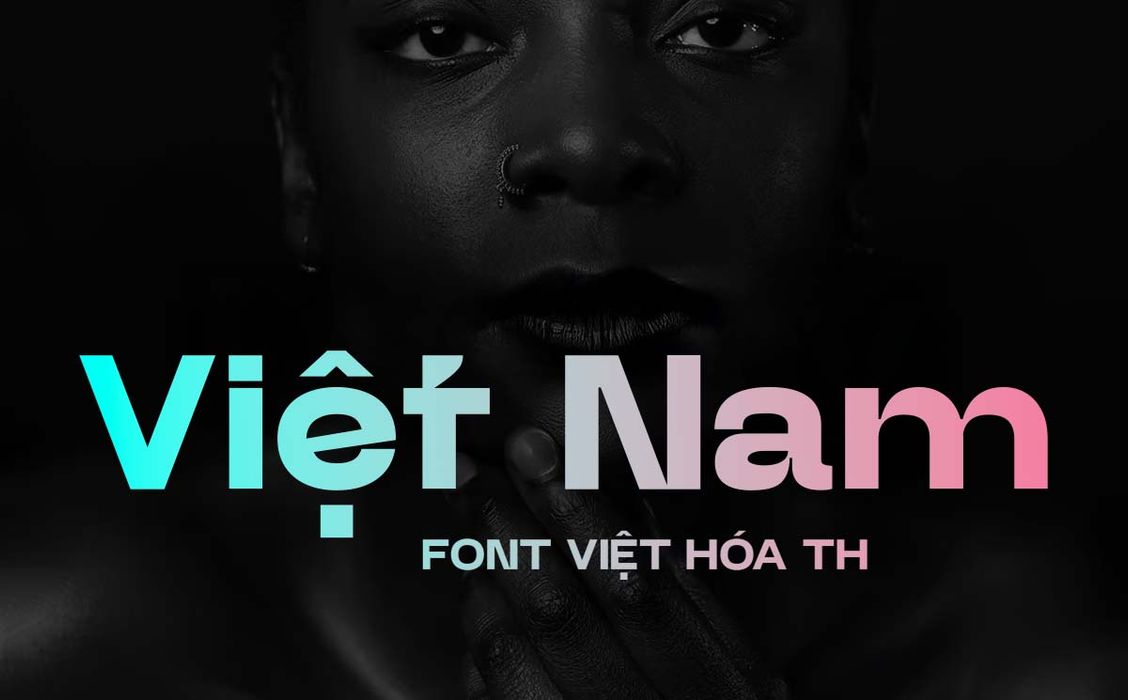
Tải font TH Legacy Sans nếu anh đang làm CV hiện đại, hồ sơ ứng tuyển startup, portfolio online và profile LinkedIn. Điểm mạnh của TH Legacy Sans là sạch, rõ, dễ đọc trên cả PDF lẫn màn hình điện thoại. Với CV hoặc portfolio, font này nên được test trong một trang có đủ tên cá nhân, chức danh, kinh nghiệm, kỹ năng, dự án tiêu biểu và thông tin liên hệ.
Khi dùng TH Legacy Sans, anh nên giữ khoảng cách dòng thoáng và hạn chế nhồi chữ. Nếu font được dùng cho tiêu đề tên cá nhân, phần mô tả kinh nghiệm nên đi cùng một sans-serif rõ ràng hơn. Nếu font dùng cho body, hãy kiểm tra các cụm tiếng Việt có dấu như “kinh nghiệm”, “thành tựu”, “quản lý dự án”, “hồ sơ năng lực” ở kích thước nhỏ.
2. TH Guton - CV nhiều cấp thông tin, portfolio freelancer và hồ sơ năng lực dài trang
Tải font TH Guton nếu anh đang làm CV nhiều cấp thông tin, portfolio freelancer và hồ sơ năng lực dài trang. Điểm mạnh của TH Guton là có nhiều style Regular, Medium, Bold, Black nên rất tiện để phân cấp nội dung. Với CV hoặc portfolio, font này nên được test trong một trang có đủ tên cá nhân, chức danh, kinh nghiệm, kỹ năng, dự án tiêu biểu và thông tin liên hệ.
Khi dùng TH Guton, anh nên giữ khoảng cách dòng thoáng và hạn chế nhồi chữ. Nếu font được dùng cho tiêu đề tên cá nhân, phần mô tả kinh nghiệm nên đi cùng một sans-serif rõ ràng hơn. Nếu font dùng cho body, hãy kiểm tra các cụm tiếng Việt có dấu như “kinh nghiệm”, “thành tựu”, “quản lý dự án”, “hồ sơ năng lực” ở kích thước nhỏ.
3. TH Cameo Sans - CV thanh lịch, hồ sơ cá nhân ngành dịch vụ, giáo dục và marketing
Tải font TH Cameo Sans nếu anh đang làm CV thanh lịch, hồ sơ cá nhân ngành dịch vụ, giáo dục và marketing. Điểm mạnh của TH Cameo Sans là giữ được sự chuyên nghiệp nhưng không quá khô. Với CV hoặc portfolio, font này nên được test trong một trang có đủ tên cá nhân, chức danh, kinh nghiệm, kỹ năng, dự án tiêu biểu và thông tin liên hệ.
Khi dùng TH Cameo Sans, anh nên giữ khoảng cách dòng thoáng và hạn chế nhồi chữ. Nếu font được dùng cho tiêu đề tên cá nhân, phần mô tả kinh nghiệm nên đi cùng một sans-serif rõ ràng hơn. Nếu font dùng cho body, hãy kiểm tra các cụm tiếng Việt có dấu như “kinh nghiệm”, “thành tựu”, “quản lý dự án”, “hồ sơ năng lực” ở kích thước nhỏ.
4. TH Manisans - profile chuyên gia, hồ sơ tư vấn, CV quản lý và portfolio cao cấp
Tải font TH Manisans nếu anh đang làm profile chuyên gia, hồ sơ tư vấn, CV quản lý và portfolio cao cấp. Điểm mạnh của TH Manisans là hiện đại, sang vừa phải, hợp với bố cục nhiều khoảng trắng. Với CV hoặc portfolio, font này nên được test trong một trang có đủ tên cá nhân, chức danh, kinh nghiệm, kỹ năng, dự án tiêu biểu và thông tin liên hệ.
Khi dùng TH Manisans, anh nên giữ khoảng cách dòng thoáng và hạn chế nhồi chữ. Nếu font được dùng cho tiêu đề tên cá nhân, phần mô tả kinh nghiệm nên đi cùng một sans-serif rõ ràng hơn. Nếu font dùng cho body, hãy kiểm tra các cụm tiếng Việt có dấu như “kinh nghiệm”, “thành tựu”, “quản lý dự án”, “hồ sơ năng lực” ở kích thước nhỏ.
5. TH Cemains - CV ngành giáo dục, coaching, chăm sóc khách hàng và nội dung cộng đồng
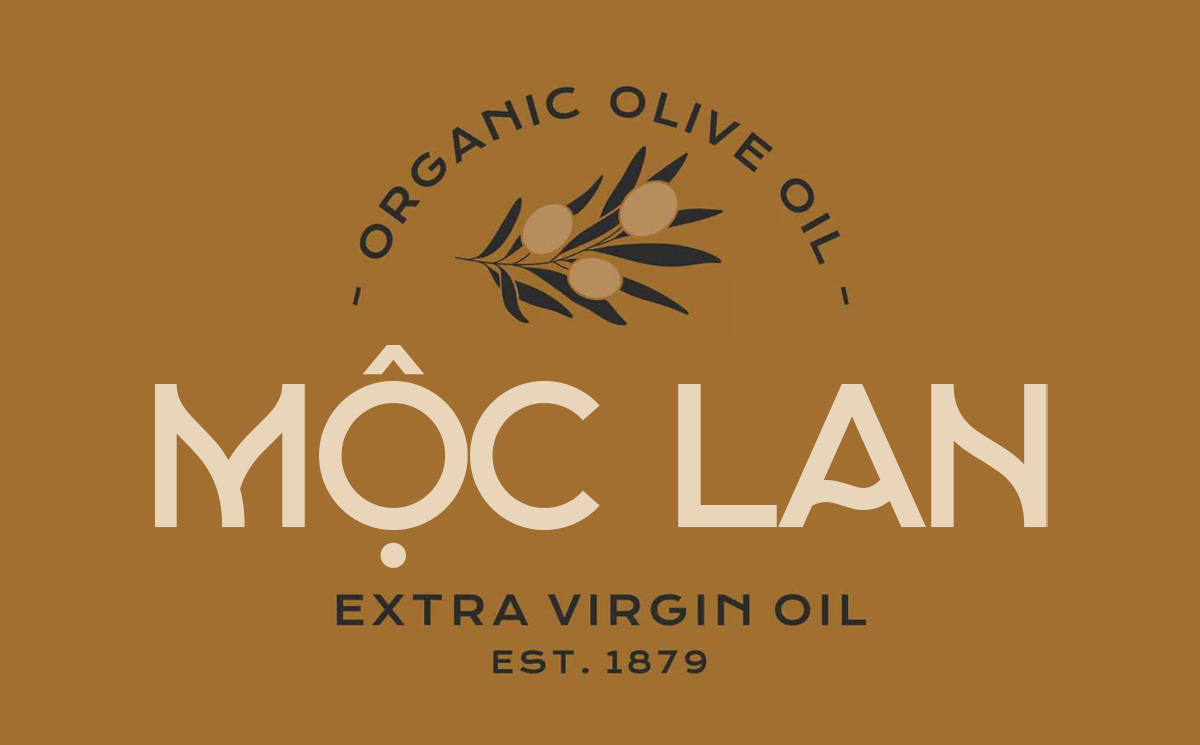
Tải font TH Cemains nếu anh đang làm CV ngành giáo dục, coaching, chăm sóc khách hàng và nội dung cộng đồng. Điểm mạnh của TH Cemains là mềm, dễ tiếp cận, tạo cảm giác tin cậy và thân thiện. Với CV hoặc portfolio, font này nên được test trong một trang có đủ tên cá nhân, chức danh, kinh nghiệm, kỹ năng, dự án tiêu biểu và thông tin liên hệ.
Khi dùng TH Cemains, anh nên giữ khoảng cách dòng thoáng và hạn chế nhồi chữ. Nếu font được dùng cho tiêu đề tên cá nhân, phần mô tả kinh nghiệm nên đi cùng một sans-serif rõ ràng hơn. Nếu font dùng cho body, hãy kiểm tra các cụm tiếng Việt có dấu như “kinh nghiệm”, “thành tựu”, “quản lý dự án”, “hồ sơ năng lực” ở kích thước nhỏ.
6. TH Artega - CV tối giản, portfolio UI/UX, hồ sơ sản phẩm và case study digital
-20250815-072440.jpg)
Tải font TH Artega nếu anh đang làm CV tối giản, portfolio UI/UX, hồ sơ sản phẩm và case study digital. Điểm mạnh của TH Artega là tối giản, gọn gàng, giúp nội dung nhìn có cấu trúc. Với CV hoặc portfolio, font này nên được test trong một trang có đủ tên cá nhân, chức danh, kinh nghiệm, kỹ năng, dự án tiêu biểu và thông tin liên hệ.
Khi dùng TH Artega, anh nên giữ khoảng cách dòng thoáng và hạn chế nhồi chữ. Nếu font được dùng cho tiêu đề tên cá nhân, phần mô tả kinh nghiệm nên đi cùng một sans-serif rõ ràng hơn. Nếu font dùng cho body, hãy kiểm tra các cụm tiếng Việt có dấu như “kinh nghiệm”, “thành tựu”, “quản lý dự án”, “hồ sơ năng lực” ở kích thước nhỏ.
7. TH Cutta - resume nhiều mục, profile freelancer, bảng kỹ năng và phần timeline
-20250814-135946.jpg)
Tải font TH Cutta nếu anh đang làm resume nhiều mục, profile freelancer, bảng kỹ năng và phần timeline. Điểm mạnh của TH Cutta là có nhiều kiểu sans-serif để tạo hệ thống chữ đồng bộ. Với CV hoặc portfolio, font này nên được test trong một trang có đủ tên cá nhân, chức danh, kinh nghiệm, kỹ năng, dự án tiêu biểu và thông tin liên hệ.
Khi dùng TH Cutta, anh nên giữ khoảng cách dòng thoáng và hạn chế nhồi chữ. Nếu font được dùng cho tiêu đề tên cá nhân, phần mô tả kinh nghiệm nên đi cùng một sans-serif rõ ràng hơn. Nếu font dùng cho body, hãy kiểm tra các cụm tiếng Việt có dấu như “kinh nghiệm”, “thành tựu”, “quản lý dự án”, “hồ sơ năng lực” ở kích thước nhỏ.
8. TH Ervha - CV ngành công nghệ, marketing performance, startup và hồ sơ dự án
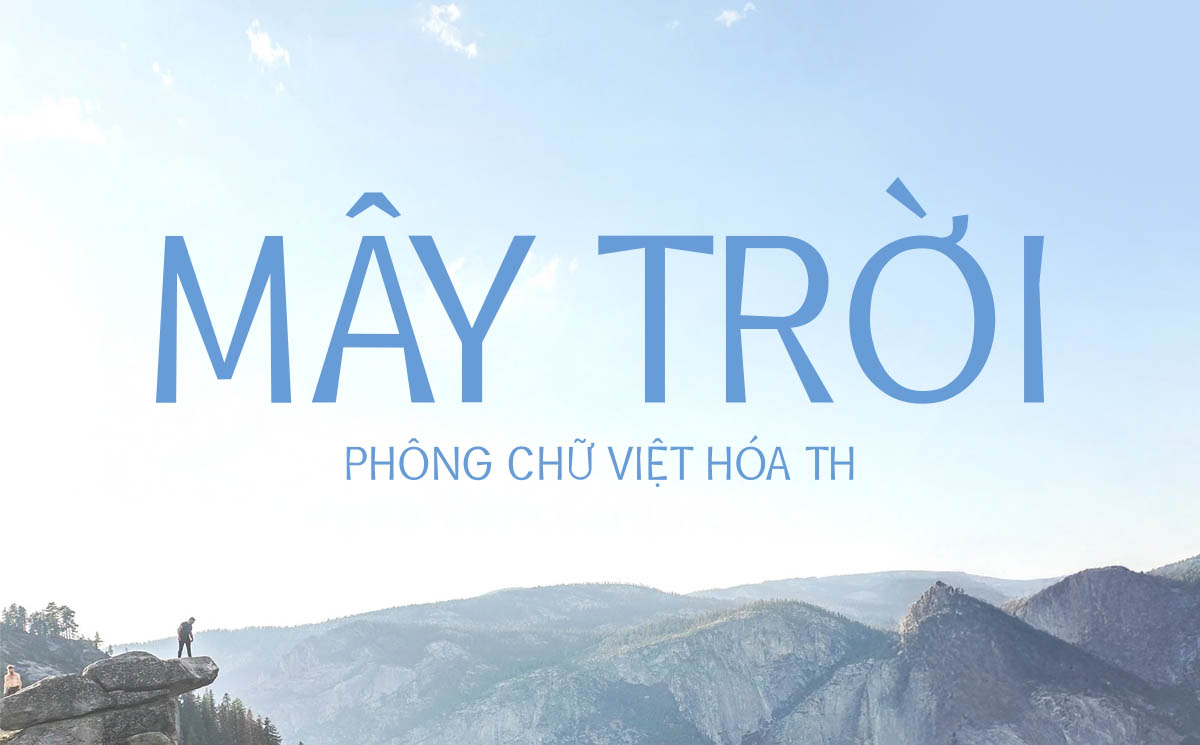
Tải font TH Ervha nếu anh đang làm CV ngành công nghệ, marketing performance, startup và hồ sơ dự án. Điểm mạnh của TH Ervha là hiện đại, gọn, không làm rối các phần nhiều số liệu. Với CV hoặc portfolio, font này nên được test trong một trang có đủ tên cá nhân, chức danh, kinh nghiệm, kỹ năng, dự án tiêu biểu và thông tin liên hệ.
Khi dùng TH Ervha, anh nên giữ khoảng cách dòng thoáng và hạn chế nhồi chữ. Nếu font được dùng cho tiêu đề tên cá nhân, phần mô tả kinh nghiệm nên đi cùng một sans-serif rõ ràng hơn. Nếu font dùng cho body, hãy kiểm tra các cụm tiếng Việt có dấu như “kinh nghiệm”, “thành tựu”, “quản lý dự án”, “hồ sơ năng lực” ở kích thước nhỏ.
9. TH Teknaf Sans - portfolio kỹ thuật, hồ sơ năng lực agency và case study có dữ liệu
-20250816-074413.jpg)
Tải font TH Teknaf Sans nếu anh đang làm portfolio kỹ thuật, hồ sơ năng lực agency và case study có dữ liệu. Điểm mạnh của TH Teknaf Sans là mạnh hơn nhóm sans thông thường, hợp với tiêu đề section và số liệu nổi bật. Với CV hoặc portfolio, font này nên được test trong một trang có đủ tên cá nhân, chức danh, kinh nghiệm, kỹ năng, dự án tiêu biểu và thông tin liên hệ.
Khi dùng TH Teknaf Sans, anh nên giữ khoảng cách dòng thoáng và hạn chế nhồi chữ. Nếu font được dùng cho tiêu đề tên cá nhân, phần mô tả kinh nghiệm nên đi cùng một sans-serif rõ ràng hơn. Nếu font dùng cho body, hãy kiểm tra các cụm tiếng Việt có dấu như “kinh nghiệm”, “thành tựu”, “quản lý dự án”, “hồ sơ năng lực” ở kích thước nhỏ.
10. TH Waking - portfolio creative, CV ngành truyền thông, thương hiệu cá nhân cao cấp
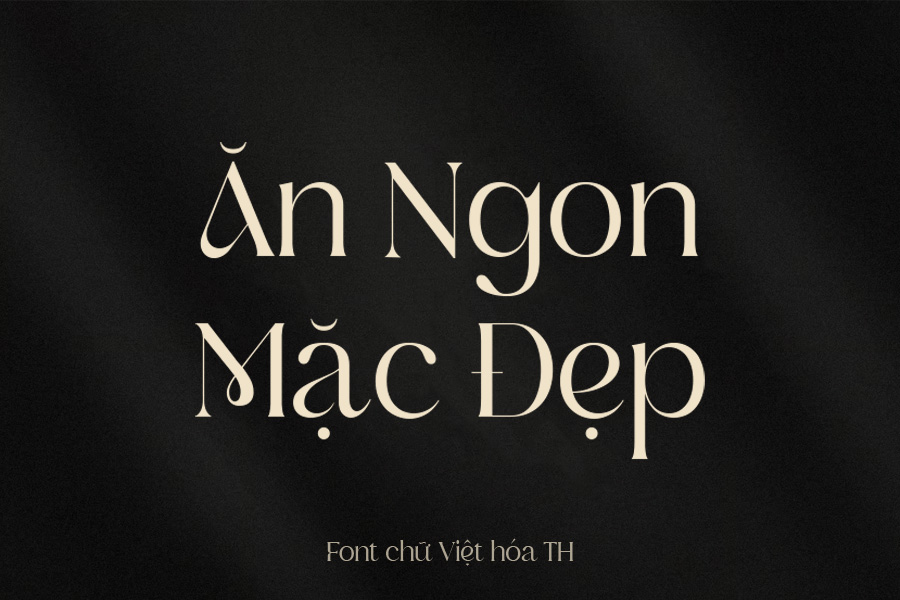
Tải font TH Waking nếu anh đang làm portfolio creative, CV ngành truyền thông, thương hiệu cá nhân cao cấp. Điểm mạnh của TH Waking là serif hiện đại, giúp tên cá nhân hoặc heading lớn có chiều sâu hơn. Với CV hoặc portfolio, font này nên được test trong một trang có đủ tên cá nhân, chức danh, kinh nghiệm, kỹ năng, dự án tiêu biểu và thông tin liên hệ.
Khi dùng TH Waking, anh nên giữ khoảng cách dòng thoáng và hạn chế nhồi chữ. Nếu font được dùng cho tiêu đề tên cá nhân, phần mô tả kinh nghiệm nên đi cùng một sans-serif rõ ràng hơn. Nếu font dùng cho body, hãy kiểm tra các cụm tiếng Việt có dấu như “kinh nghiệm”, “thành tựu”, “quản lý dự án”, “hồ sơ năng lực” ở kích thước nhỏ.
11. TH Marlino - hồ sơ học thuật, CV biên tập, tư vấn, nghiên cứu và luật
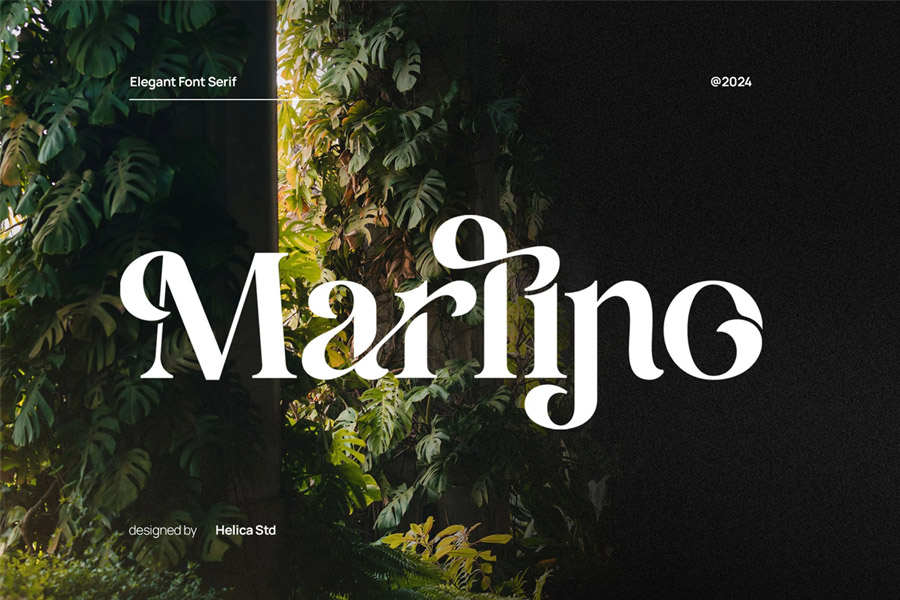
Tải font TH Marlino nếu anh đang làm hồ sơ học thuật, CV biên tập, tư vấn, nghiên cứu và luật. Điểm mạnh của TH Marlino là có chân rõ ràng, tạo cảm giác nghiêm túc và đáng tin. Với CV hoặc portfolio, font này nên được test trong một trang có đủ tên cá nhân, chức danh, kinh nghiệm, kỹ năng, dự án tiêu biểu và thông tin liên hệ.
Khi dùng TH Marlino, anh nên giữ khoảng cách dòng thoáng và hạn chế nhồi chữ. Nếu font được dùng cho tiêu đề tên cá nhân, phần mô tả kinh nghiệm nên đi cùng một sans-serif rõ ràng hơn. Nếu font dùng cho body, hãy kiểm tra các cụm tiếng Việt có dấu như “kinh nghiệm”, “thành tựu”, “quản lý dự án”, “hồ sơ năng lực” ở kích thước nhỏ.
12. TH Runsling - portfolio cá nhân, media kit, profile consultant và freelancer premium
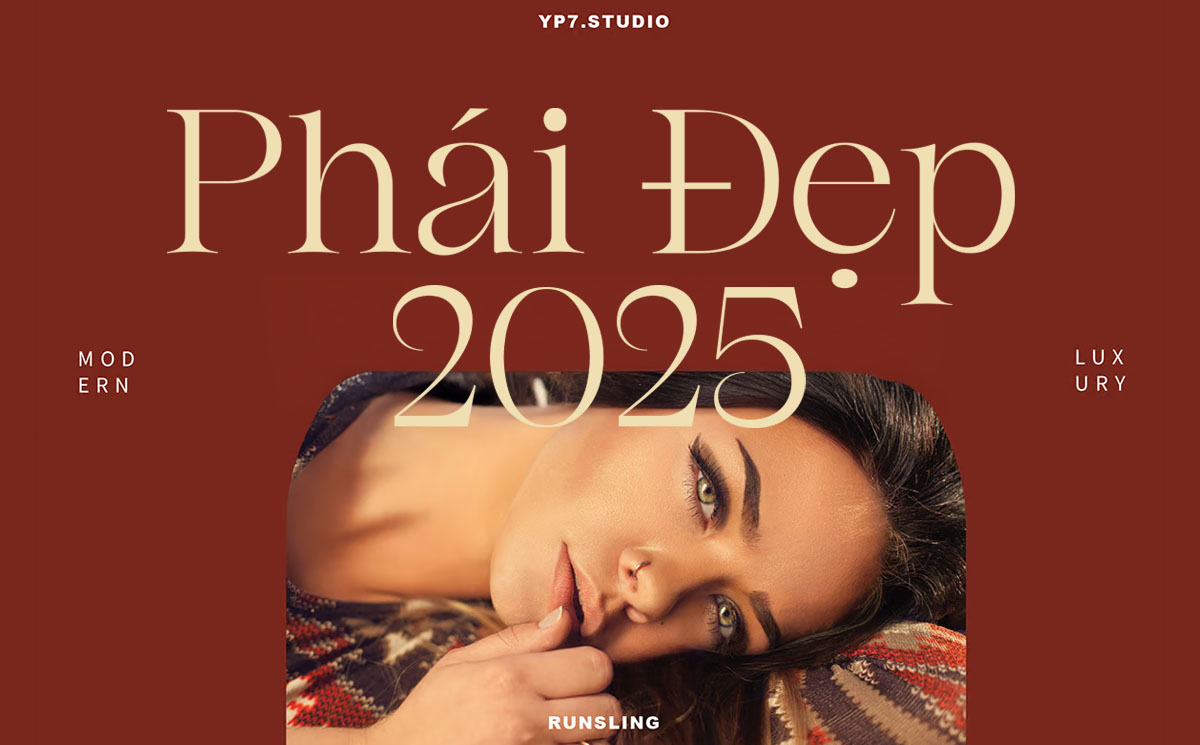
Tải font TH Runsling nếu anh đang làm portfolio cá nhân, media kit, profile consultant và freelancer premium. Điểm mạnh của TH Runsling là thanh lịch, hợp khi muốn hồ sơ có gu mà vẫn không quá phô. Với CV hoặc portfolio, font này nên được test trong một trang có đủ tên cá nhân, chức danh, kinh nghiệm, kỹ năng, dự án tiêu biểu và thông tin liên hệ.
Khi dùng TH Runsling, anh nên giữ khoảng cách dòng thoáng và hạn chế nhồi chữ. Nếu font được dùng cho tiêu đề tên cá nhân, phần mô tả kinh nghiệm nên đi cùng một sans-serif rõ ràng hơn. Nếu font dùng cho body, hãy kiểm tra các cụm tiếng Việt có dấu như “kinh nghiệm”, “thành tựu”, “quản lý dự án”, “hồ sơ năng lực” ở kích thước nhỏ.
13. TH Okaba - portfolio designer, stylist, content creator và hồ sơ dịch vụ cá nhân
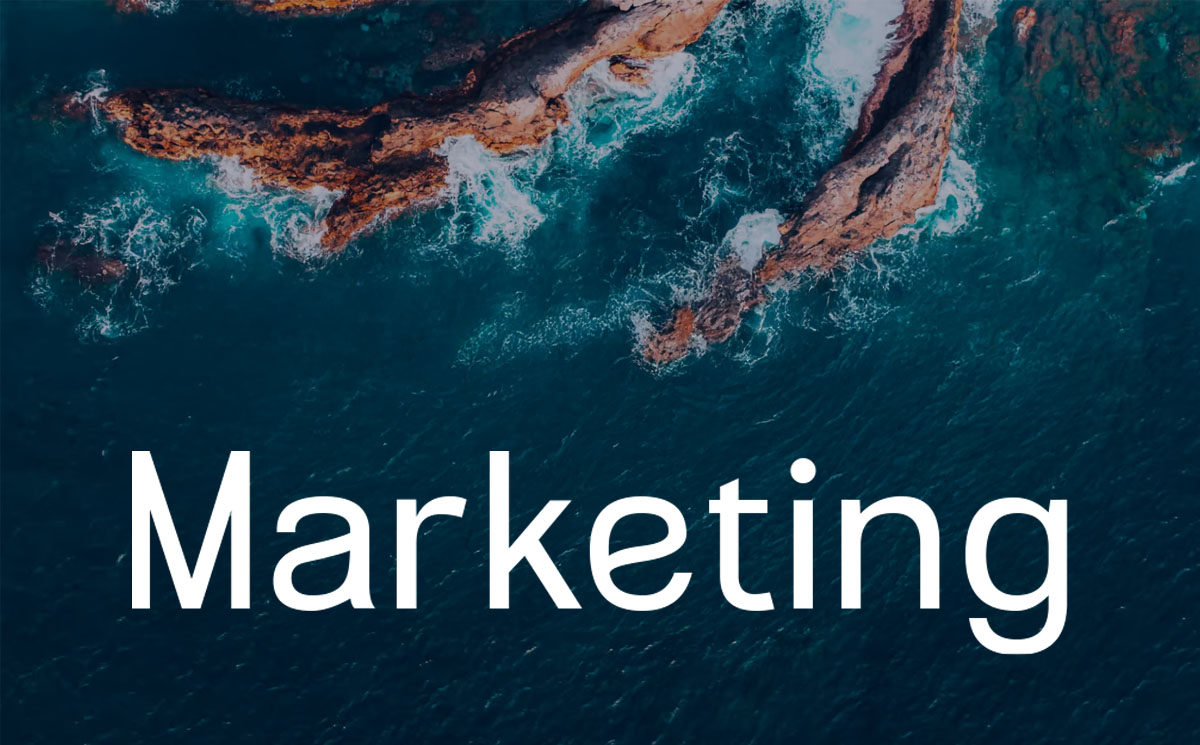
Tải font TH Okaba nếu anh đang làm portfolio designer, stylist, content creator và hồ sơ dịch vụ cá nhân. Điểm mạnh của TH Okaba là có chất boutique, dùng tốt cho tên portfolio hoặc tiêu đề case study. Với CV hoặc portfolio, font này nên được test trong một trang có đủ tên cá nhân, chức danh, kinh nghiệm, kỹ năng, dự án tiêu biểu và thông tin liên hệ.
Khi dùng TH Okaba, anh nên giữ khoảng cách dòng thoáng và hạn chế nhồi chữ. Nếu font được dùng cho tiêu đề tên cá nhân, phần mô tả kinh nghiệm nên đi cùng một sans-serif rõ ràng hơn. Nếu font dùng cho body, hãy kiểm tra các cụm tiếng Việt có dấu như “kinh nghiệm”, “thành tựu”, “quản lý dự án”, “hồ sơ năng lực” ở kích thước nhỏ.
14. TH Minoruca - portfolio nghệ thuật, branding, nhiếp ảnh, thời trang và lifestyle
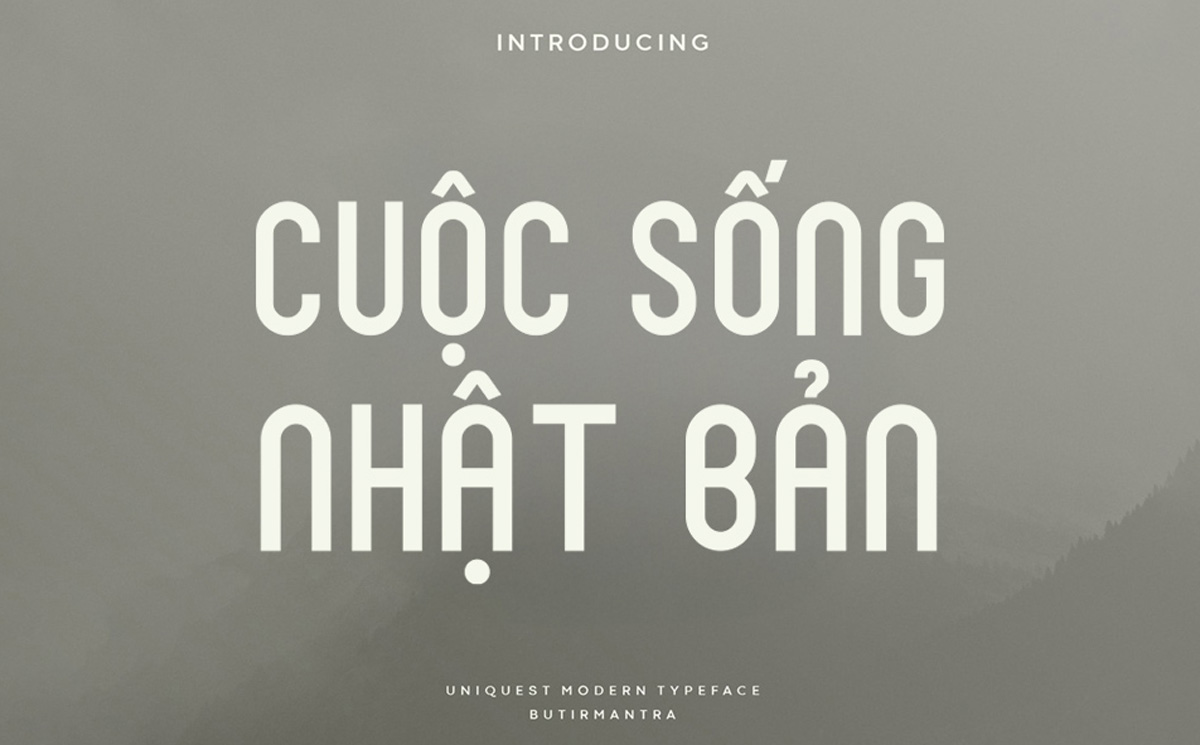
Tải font TH Minoruca nếu anh đang làm portfolio nghệ thuật, branding, nhiếp ảnh, thời trang và lifestyle. Điểm mạnh của TH Minoruca là mềm và sang, phù hợp với bố cục nhiều hình ảnh. Với CV hoặc portfolio, font này nên được test trong một trang có đủ tên cá nhân, chức danh, kinh nghiệm, kỹ năng, dự án tiêu biểu và thông tin liên hệ.
Khi dùng TH Minoruca, anh nên giữ khoảng cách dòng thoáng và hạn chế nhồi chữ. Nếu font được dùng cho tiêu đề tên cá nhân, phần mô tả kinh nghiệm nên đi cùng một sans-serif rõ ràng hơn. Nếu font dùng cho body, hãy kiểm tra các cụm tiếng Việt có dấu như “kinh nghiệm”, “thành tựu”, “quản lý dự án”, “hồ sơ năng lực” ở kích thước nhỏ.
15. TH Sweets Holly - chữ ký cá nhân, tagline freelancer và điểm nhấn ở trang cuối portfolio
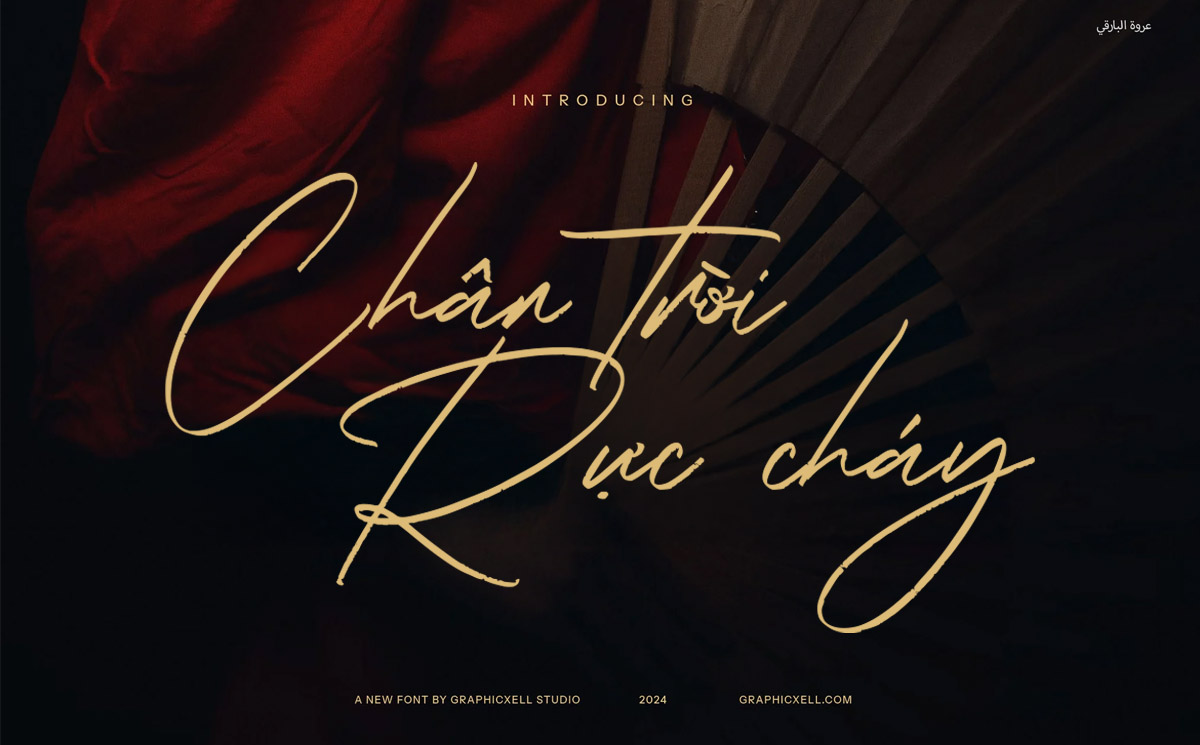
Tải font TH Sweets Holly nếu anh đang làm chữ ký cá nhân, tagline freelancer và điểm nhấn ở trang cuối portfolio. Điểm mạnh của TH Sweets Holly là mang cảm giác signature, giúp hồ sơ có dấu ấn riêng nếu dùng tiết chế. Với CV hoặc portfolio, font này nên được test trong một trang có đủ tên cá nhân, chức danh, kinh nghiệm, kỹ năng, dự án tiêu biểu và thông tin liên hệ.
Khi dùng TH Sweets Holly, anh nên giữ khoảng cách dòng thoáng và hạn chế nhồi chữ. Nếu font được dùng cho tiêu đề tên cá nhân, phần mô tả kinh nghiệm nên đi cùng một sans-serif rõ ràng hơn. Nếu font dùng cho body, hãy kiểm tra các cụm tiếng Việt có dấu như “kinh nghiệm”, “thành tựu”, “quản lý dự án”, “hồ sơ năng lực” ở kích thước nhỏ.
Cách phối font để CV nhìn chuyên nghiệp hơn
1. Chỉ dùng 1-2 font chính
Một CV tốt không cần quá nhiều kiểu chữ. Anh có thể dùng một font sans-serif cho toàn bộ nội dung, rồi tạo phân cấp bằng bold, size và màu. Nếu muốn có chất cá nhân hơn, hãy thêm một font serif cho tên hoặc headline, nhưng đừng đổi font ở từng section. Sự nhất quán làm hồ sơ nhìn đắt hơn rất nhiều.
2. Ưu tiên độ đọc cho phần kinh nghiệm và kỹ năng
Nhà tuyển dụng hoặc khách hàng thường đọc kỹ các phần như kinh nghiệm, dự án, kỹ năng, kết quả, công cụ sử dụng và thông tin liên hệ. Các phần này nên dùng font rõ, không quá mảnh, không quá trang trí. Font đẹp nhưng khó đọc sẽ làm hồ sơ mất điểm nhanh hơn anh nghĩ.
3. Portfolio có thể cá tính hơn CV, nhưng vẫn cần trật tự
Portfolio freelancer cần thể hiện phong cách cá nhân, nhất là với designer, content creator, photographer, marketer hoặc consultant. Tuy nhiên, phần case study vẫn cần trật tự: bối cảnh, vai trò, giải pháp, kết quả. Font cá tính nên nằm ở cover, title dự án hoặc quote; phần mô tả nên sạch và dễ theo dõi.
Gợi ý chọn nhanh theo ngành nghề
Nếu làm CV ứng tuyển công nghệ, startup, marketing hoặc vận hành, hãy thử TH Legacy Sans, TH Guton, TH Artega, TH Cutta, TH Ervha hoặc TH Teknaf Sans. Nếu làm hồ sơ chuyên gia, consultant, giáo dục, luật, nghiên cứu hoặc quản lý, TH Manisans, TH Cameo Sans, TH Cemains, TH Marlino và TH Runsling sẽ phù hợp hơn. Với portfolio sáng tạo, branding, thời trang, nhiếp ảnh hoặc personal brand, TH Waking, TH Okaba, TH Minoruca và TH Sweets Holly là nhóm nên thử.
Font chữ cho CV và portfolio không chỉ là yếu tố trang trí. Nó ảnh hưởng trực tiếp đến cảm giác chuyên nghiệp, độ dễ đọc và cách người xem đánh giá năng lực của anh trong vài giây đầu tiên. Chọn đúng font giúp hồ sơ rõ hơn, có gu hơn và dễ ghi nhớ hơn.
Với 15 font TH Việt hóa trên, anh có thể xây nhiều kiểu hồ sơ: tối giản, sang trọng, sáng tạo, chuyên gia hoặc freelancer cao cấp. Hãy bắt đầu bằng một trang CV mẫu, thử font ở kích thước thật, kiểm tra dấu tiếng Việt và xuất PDF để xem trên điện thoại trước khi gửi cho nhà tuyển dụng hoặc khách hàng.